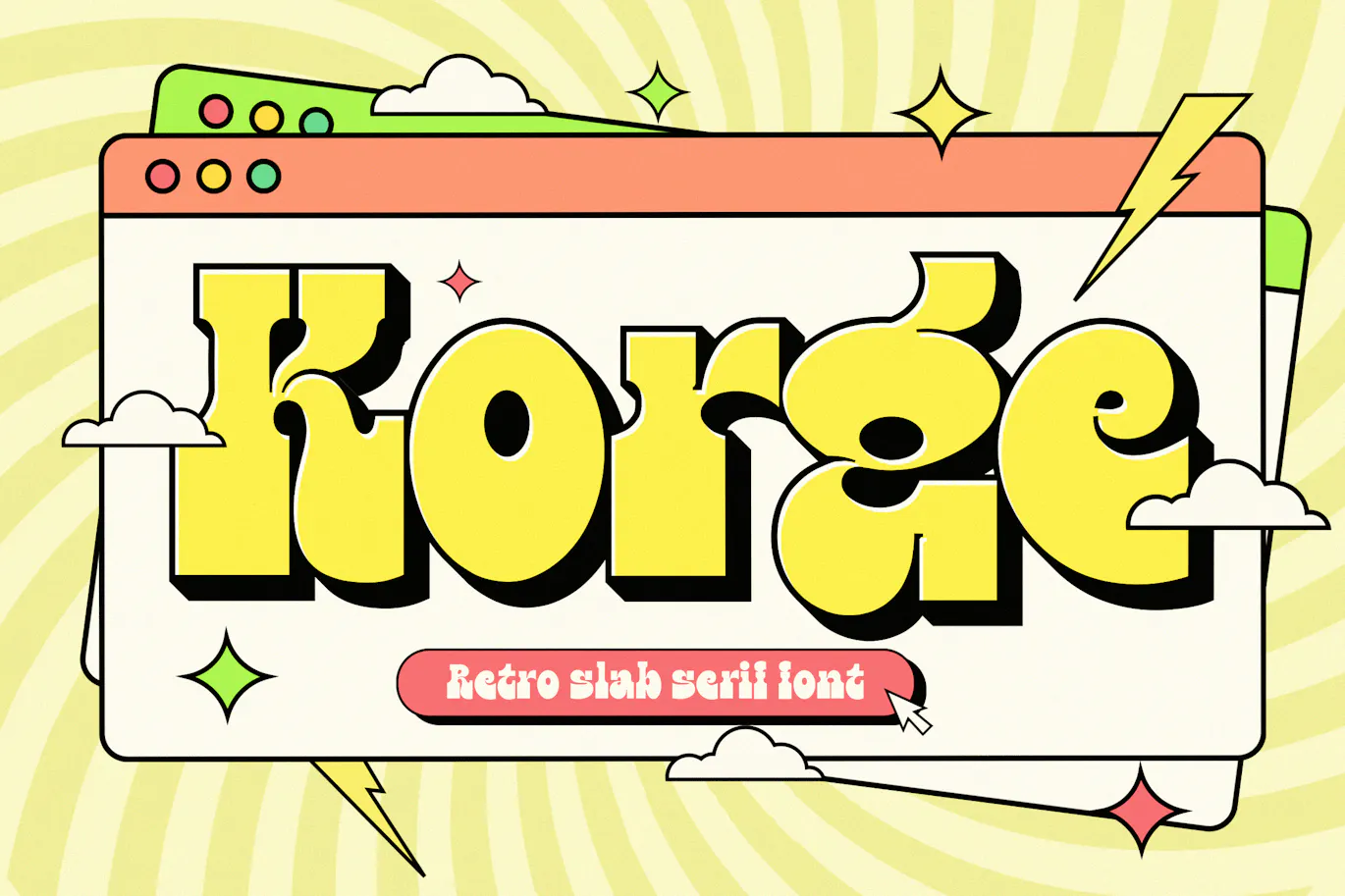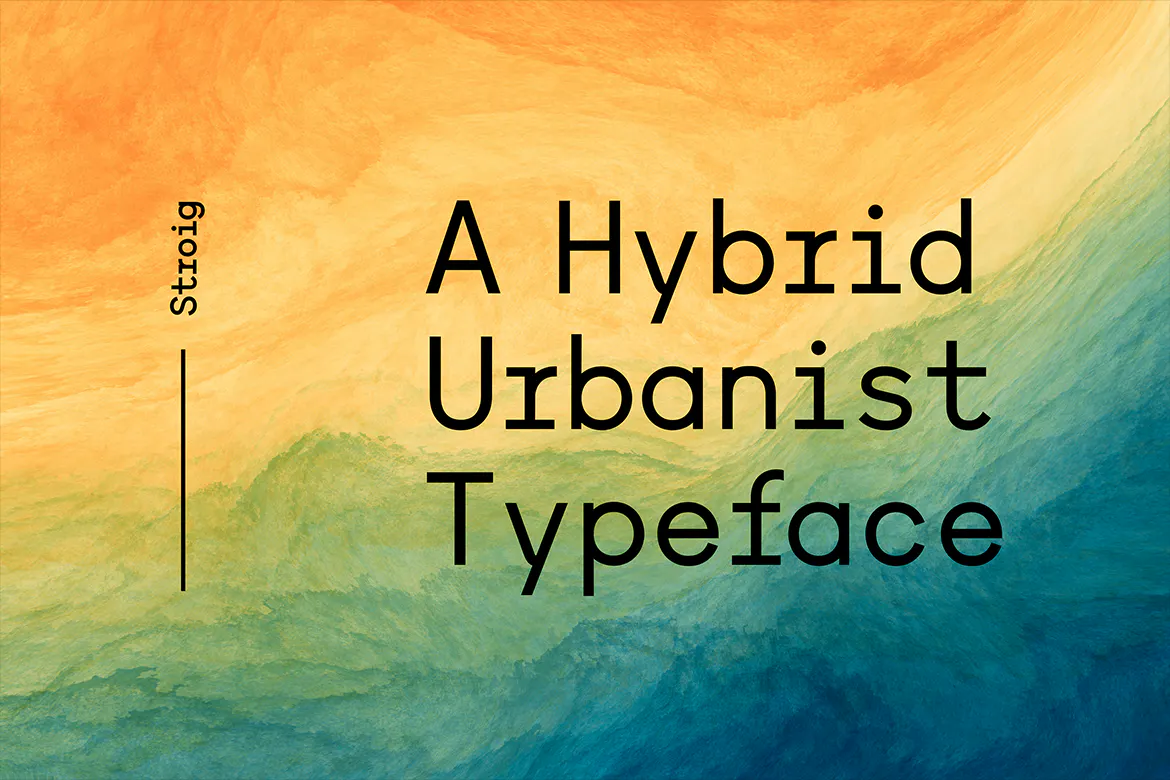
可口可乐标志风格的英文手写花体字体 – Ganglion
Ganglion是一款可口可乐标志风格的英文花体字体,散发着力量和大胆的气息,使其成为各种设计应用的出色选择。凭借其强大而大胆的字体,“Ganglion Font”引人注目并做出了强有力的声明。该字体自信的脚本风格传达了自信和权威,使其成为有影响力的标题、徽标和品牌材料的理想选择。“Ganglion Font”结构坚固,线条粗犷,给人一种稳定可靠的感觉。该字体的粗体笔画和明确的形状使其高度可见且清…- 55
粗糙仿旧元素的英文手写笔刷字体 – Foreclosure – Brush Font
Foreclosure是一款粗糙仿旧元素的英文手写笔刷字体,字体拥有纹理外观,每个字符都带有粗糙或仿旧的元素。这些纹理模仿手绘笔画的外观,赋予字体有机而真实的感觉。字体包提供了一系列的粗细和纹理,允许设计师为他们的项目选择最合适的样式。无论是寻求微妙的纹理还是严重仿旧的外观,“Foreclosure”都提供了满足各种设计需求的选项。“Foreclosure”粗犷且饱经风霜的外观赋予其超越潮流的永恒…- 602
适用于logo标志的英文粗体slab衬线字体 – Korge
“Korge”,一种迷人且多功能的复古大胆板衬线字体,将复古美学与现代功能无缝地相结合。凭借其大胆的设计、衬线形式和常规、圆形和挤压的三个版本,Korge为您的设计企业提供了丰富的创意可能性。 Korge是一种字体,可以将您的项目带回设计的黄金时代。它大胆而鲜明的衬线唤起了一种怀旧的感觉,为您的作品增添了经典而持久的吸引力。 Korge提供的不是一种,而是三种不同的风格可供选择。常规版本散发着令人…- 50
精致混合都市风格的英文无衬线字体 – Stroig
SROIG是一款精致、混合和都市风格的字体系列,非常适合为您的设计赋予优雅和沉稳的气息。这款美丽的字体将为任何项目增添一丝庄严和宏伟。这款独一无二的字体非常适合创建精美的标识并为您的文本增添一丝精致。SROIG 可用于多用途文本表示以及品牌、标识和显示目的。它特别适合创建能够吸引访问者注意力的特殊徽标、促销内容和营销图形。通过调整字体的字母间距,您可以为您的创意项目提供更多的设计选项。看一下下面的…- 45
优雅粗画笔复古的汽车标志英文连字字体 – Rindler
Rindler是一款优雅粗画笔复古的汽车标志英文连字字体,是为现代灵魂打造的复古优雅的缩影,让您的风格焕发活力。Rindler 的灵感源自老式汽车标志的流畅线条和汽车旅馆霓虹灯招牌的怀旧光芒,为您带来 1970 年代黄金时代的难忘旅程。体验Rindler无可挑剔的魅力,感受昔日的魅力。无论您是打造品牌形象还是为您的设计增添复古气息,它都是您通往永恒精致的通行证。字体格式有otf、ttf、woff、…- 52